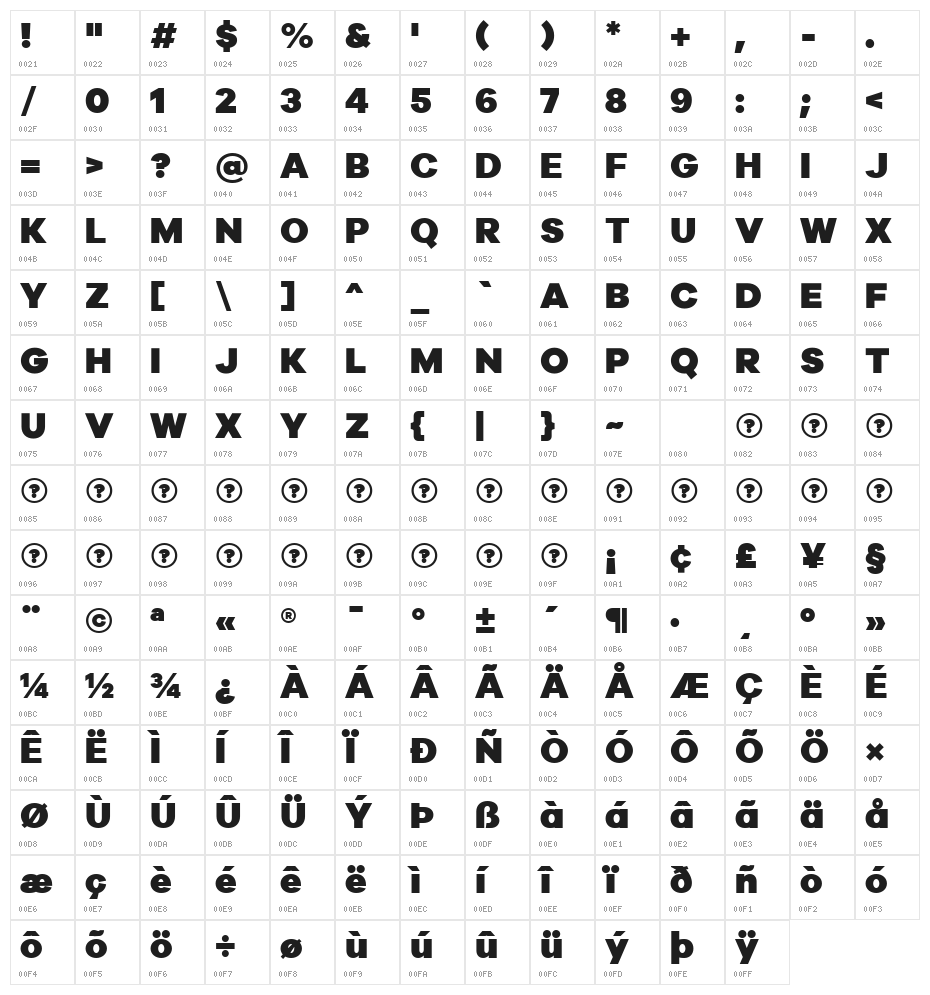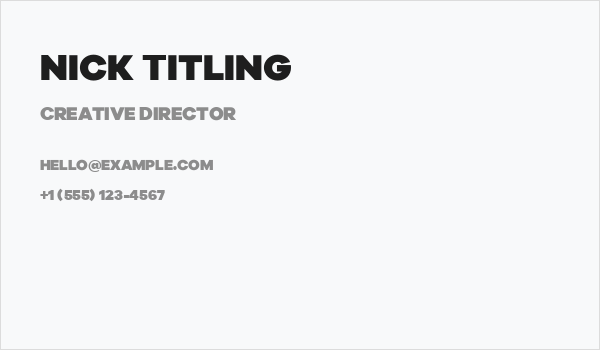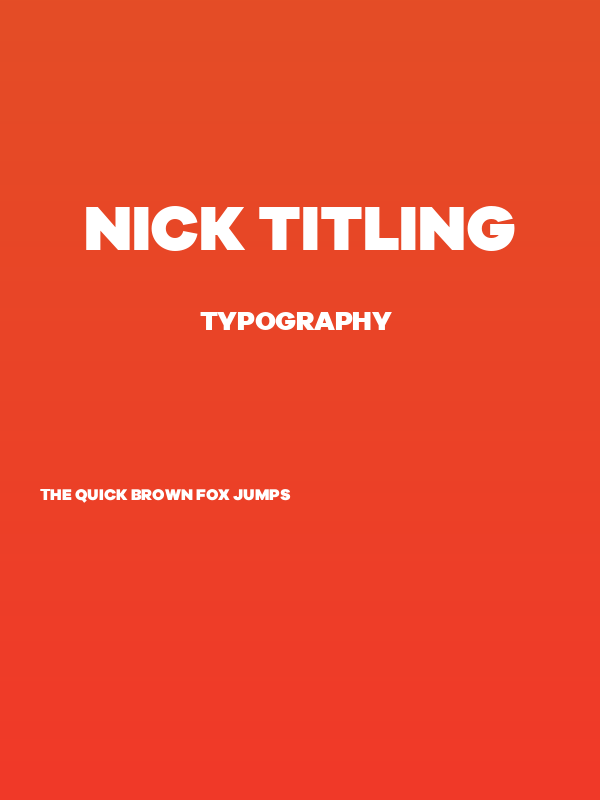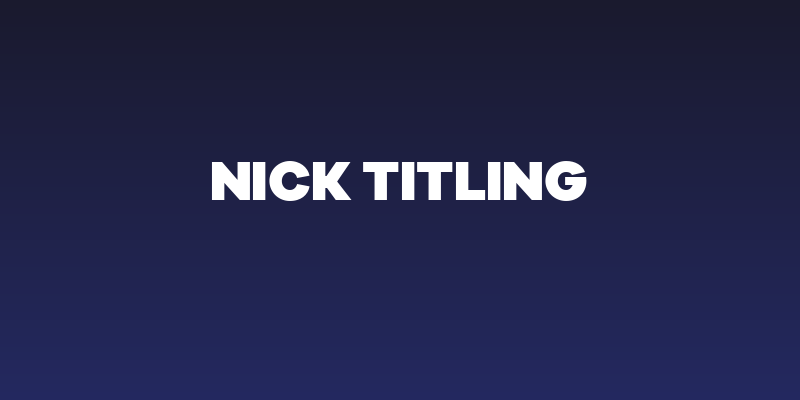
Nick Titling Font
Diese Schriftart enthält 462 Zeichen. Klicken Sie auf ein Zeichen für Details.
| Vorgeschlagene Projekte | Ideal for headlines, posters, branding, and advertising where a strong visual impact is needed. |